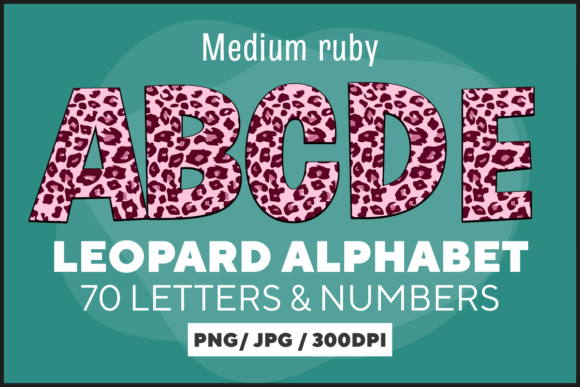
Medium Ruby Leopard Letters
適切なデザイン要素を見つけるのは難しい場合がありますが、Medium Ruby Leopard Lettersは作品を即座に引き立てる優れたコレクションを提供します。
精密に作られたMedium Ruby Leopard Lettersは、クリーンなベクター、滑らかなタイポグラフィ、そして安心のための商用ライセンスを提供します。
POD(オンデマンド印刷)製品、結婚式の招待状、またはソーシャルメディアのグラフィックを作成している場合でも、Medium Ruby Leopard Lettersは理想的です。